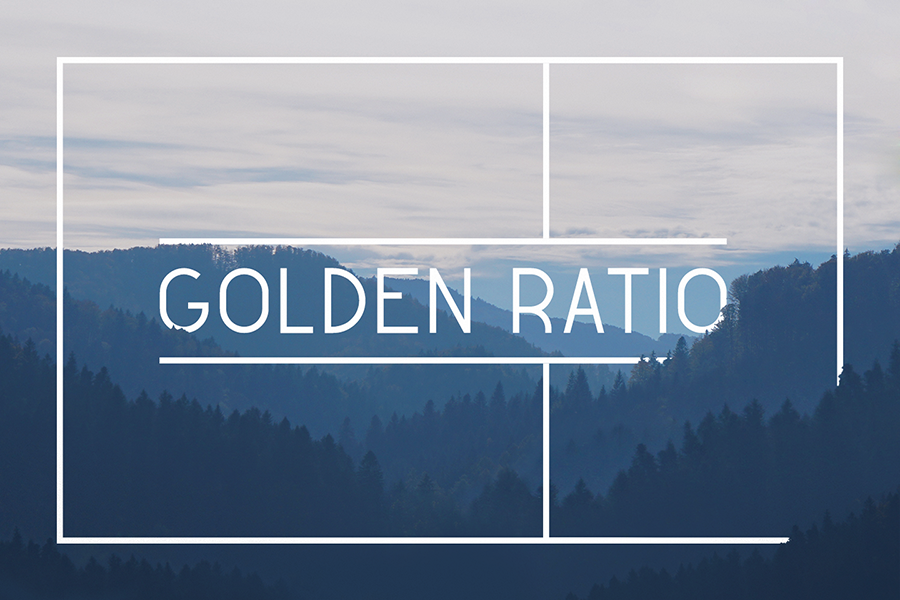
Golden Ratio Typeface é uma tipografia sans-serif desenvolvida pelo designer Valentin François que oferece três pesos diferentes para atender a uma ampla gama de aplicações visuais. Este conjunto de caracteres all caps destaca-se por sua arquitetura elegante, associada ao conceito da proporção golden ratio, um enredo geométrico fascinante presente em diversas formas da natureza e na arte humanitária. Com seus 110 caracteres disponíveis, é ideal para uso em aplicativos que exigem letramento acentuado ou quando o objetivo é destacar mensagens importantes, como nomes de marca ou slogans visuais. Para designers e desenvolvedores gráficos que buscam uma tipografia moderna e sofisticada, Golden Ratio Typeface oferece um novo nível de expressão visual com seu design simples e arredondado, enquanto mantém a força e o impacto necessários em ambientes digitais.